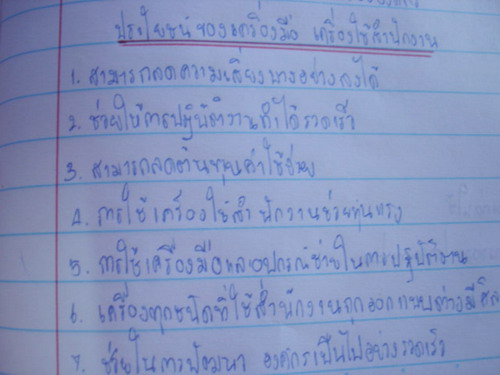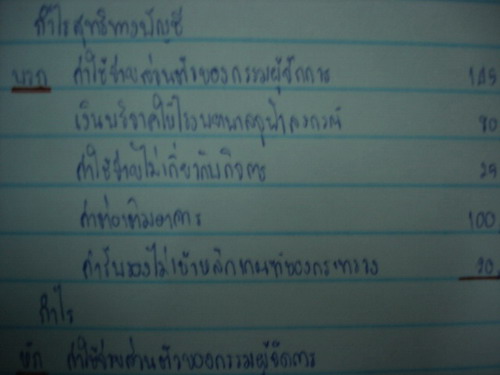
กระจู๋โชว์ลายมือ
มาโชว์มั่งสิ  :25:
อันนี้แบบจด
ิัอันนี้แบบสวยไม่เสร็จ  :04:
:25: วิชาเครื่องใช้สำนักงาน กับบัญชี
สวยไม่เสร็จ - -*  :08:
:42: เหมือนสมุดจดแบบใหญ่ที่รร.เลย
ไหนบอกลายมือน่ากลัวยะนุ๊ก น่ารักออก  :27:
เอ่ออ น่ารัก
ขอบใจว่ะเฮ้ยย  :42:
ลายมือเอ็งก็ล้อ หล่อ
ล่อซะตูมึน  :32:
ลายมือล้อ ... หล่อ  :42:
ลายมือเร่ ต้องแบบ อภิมหา โค-ต-ร- หล่อ  :18:
ลายมือผมสวยนะเว้ยครับ  :07:
อ่านลายมือเร่ไม่ออกครับ
ภาษาไทย
ภาษาอังกฤษ
(เค้าบังคับเขียนตัวเขียน  :05:)
ไม่สวยเหมือนที่หนิงว่าเลย  :42:
ลายมือการ์ตูน แบบสวยอะไหม น่ารัก  :25:
ส่วนภาษาอังกฤษ เลิกเขียนตัวเขียนตั้งแต่ขึ้นม.4เป็นต้นไป  :42: